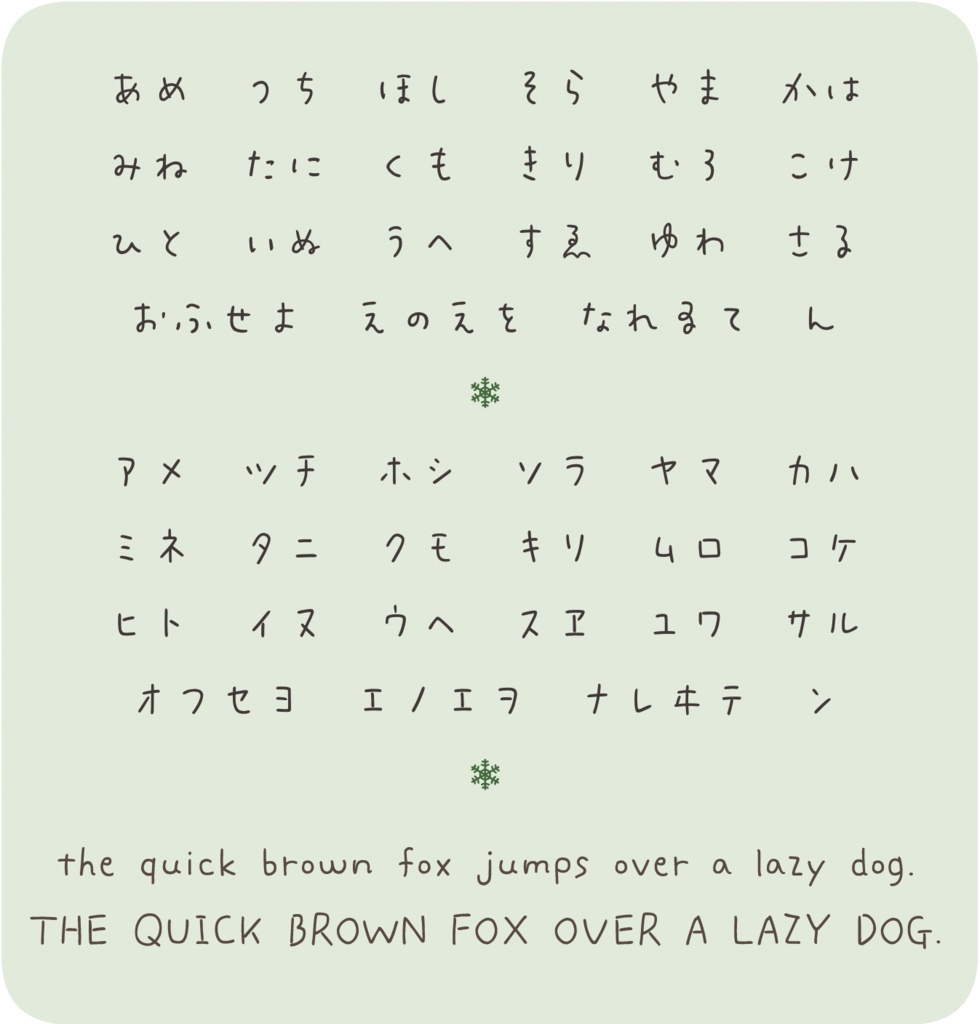
フォント「風花Pro」
フォント「風花Pro」は、流れるような線が特徴の手書き風フォントです。 こちらのPro版は商用使用可能です。 動作確認をご希望の方は、無料の教漢版(商用は不可)をお試しいただいてからご購入ください。 ↓こちらのサイトで無料版を配布しています http://cotorifont.net 禁止事項や詳しい使用規約などは、サイトのFAQをご覧ください。 http://cotorifont.net/font01/kazahana/faq.htm 【収録文字】 ●ひらがな●全角・半角カタカナ●全角/半角アルファベット ●全角/半角数字 ●ギリシャ文字●ロシア文字●各種記号 ●JIS第1水準漢字 ●JIS第2水準漢字の一部(3390字中2647字に対応) ●IBM拡張漢字の一部(388字中294字に対応) ●プラスα(JIS第3水準以降の漢字のごく一部) 「風花Pro」は glyphsapp.com さんのGlyphsを使って作成しました。